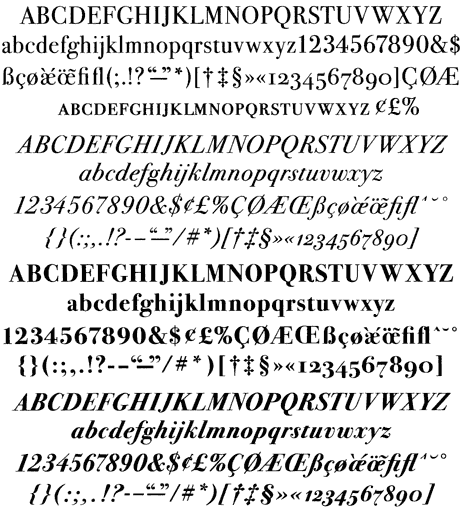
Историческая версия шрифта Бодони фирмы ITC сделанная в 1994 году группа дизайнеров под руководством Самнера Стоуна (Sumner Stone) на основе изучения сохранившихся шрифтов Бодони и их оттисков. Цифровой вариант под названием ITC Bodoni, воспроизводит реальные рисунки Бодони для кеглей 6, 12 и 72 (на рисунке ITC Bodoni 72). |